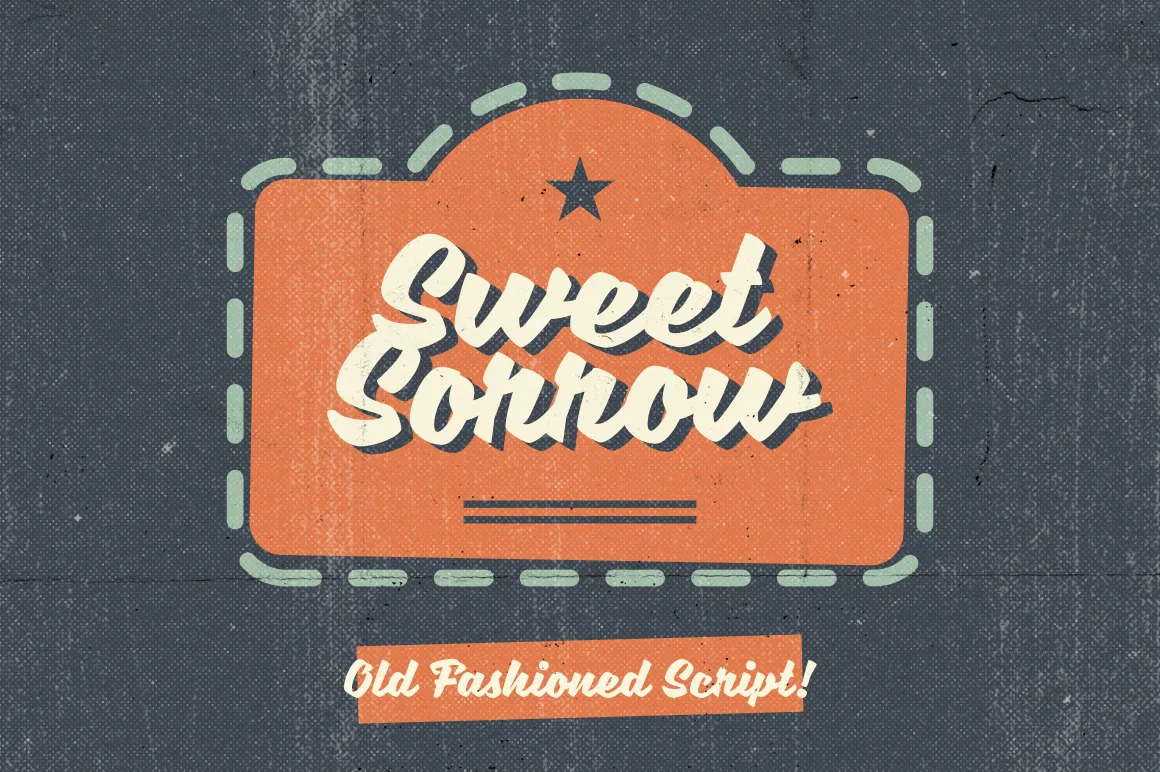
Sweet Sorrow é uma fonte serifada que traz para você um toque nostálgico, perfeito para adicionar um toque vintage ou retrô a seus projetos digitais. Inspirado nas famosas placas de 1950s com suas linhas curvas modernizadas e arredondamentos únicos, esta fonte é uma viagem através do tempo no campo da tipografia. Ideal para rótulos de loja, design gráfico vintage, t-shirts personalizadas ou qualquer projeto que valorize a estética dos tempos antigos. Disponível em formatos OTF e TTF, vem com algumas ligaturas inclusas para garantir uma beleza única à sua fonte. Ideal para designers buscando um toque especial em seus designs.